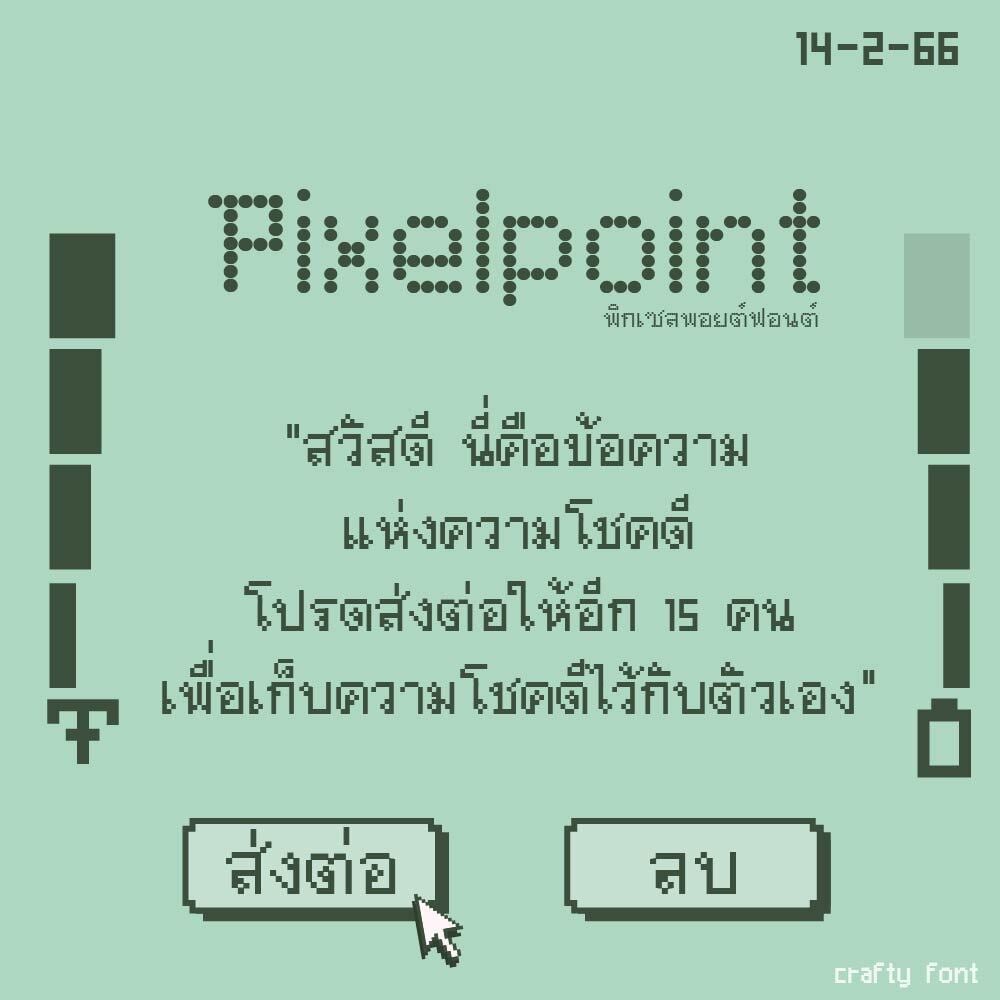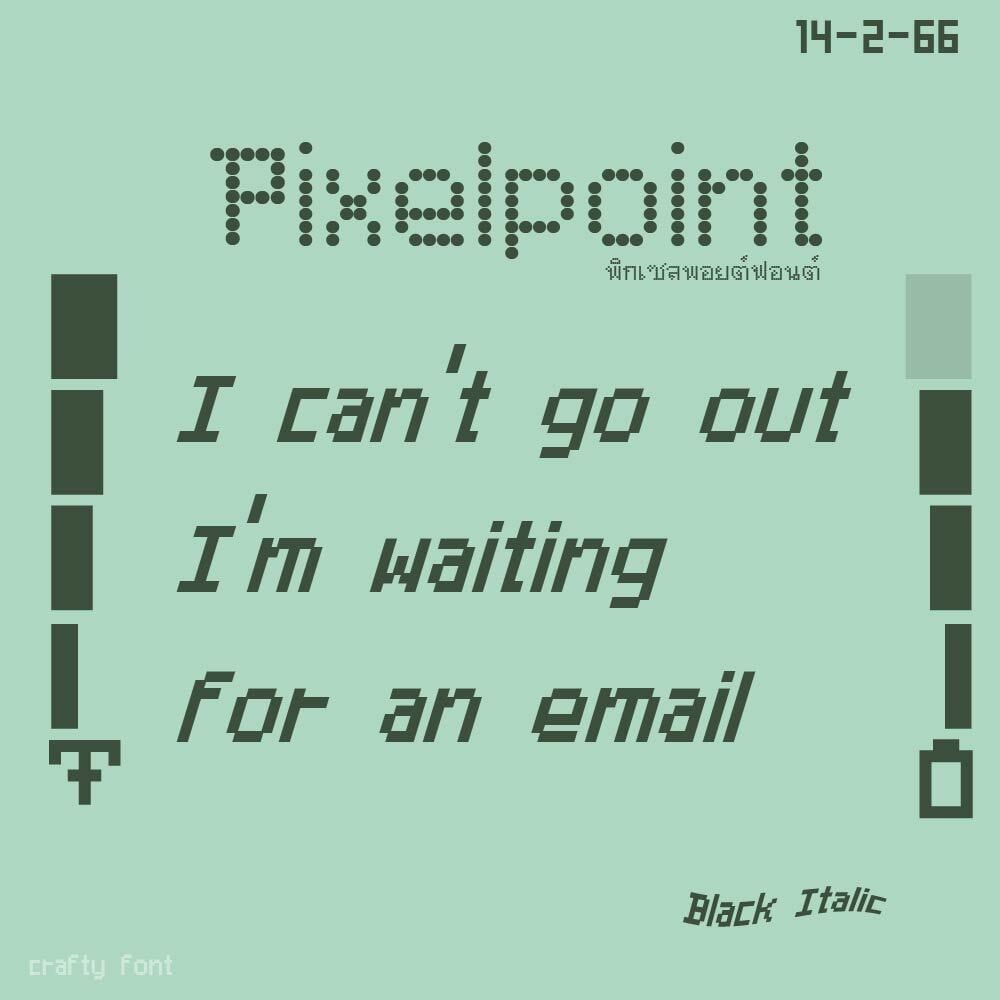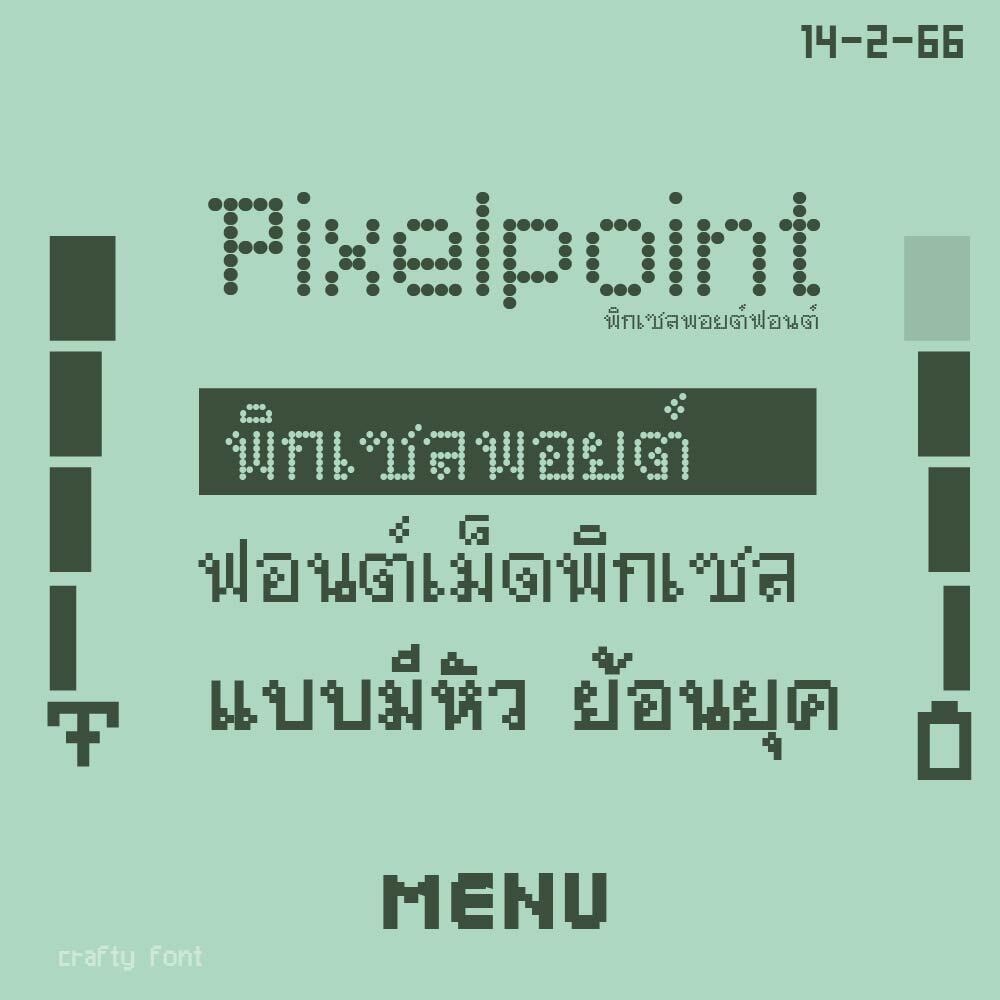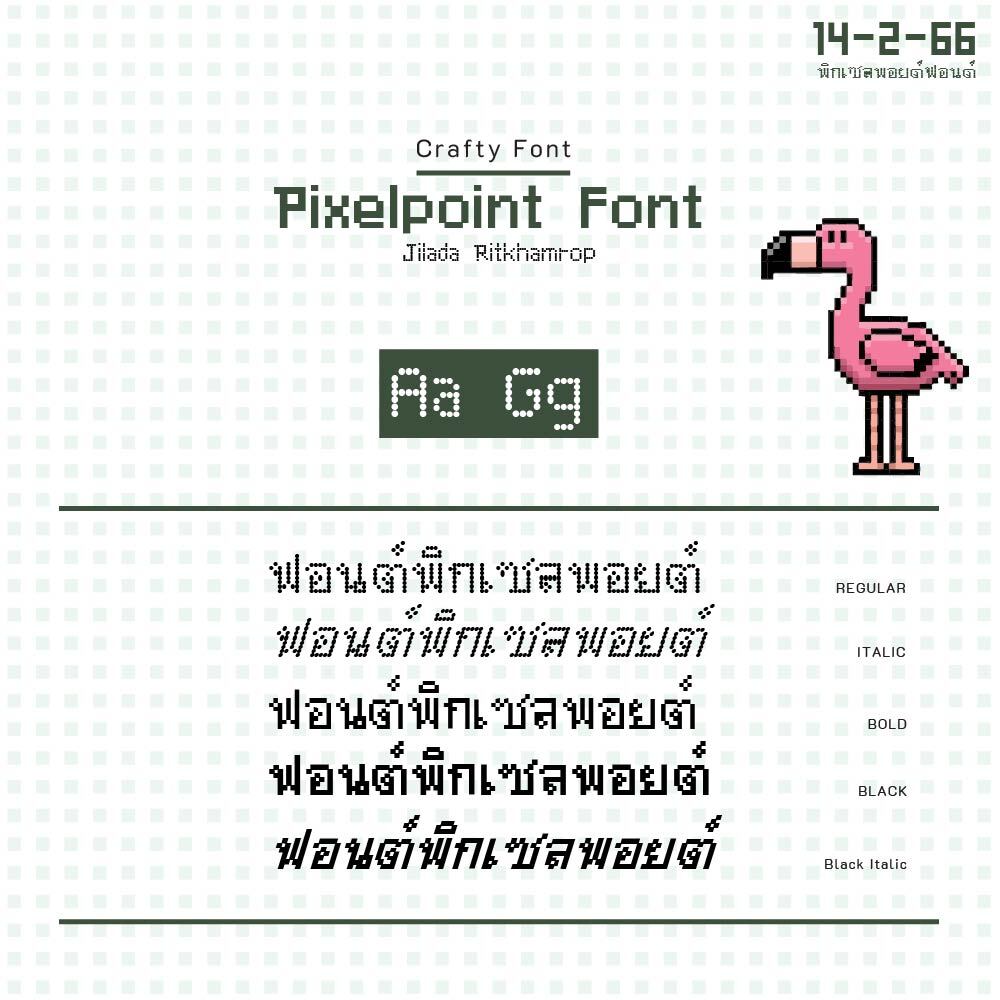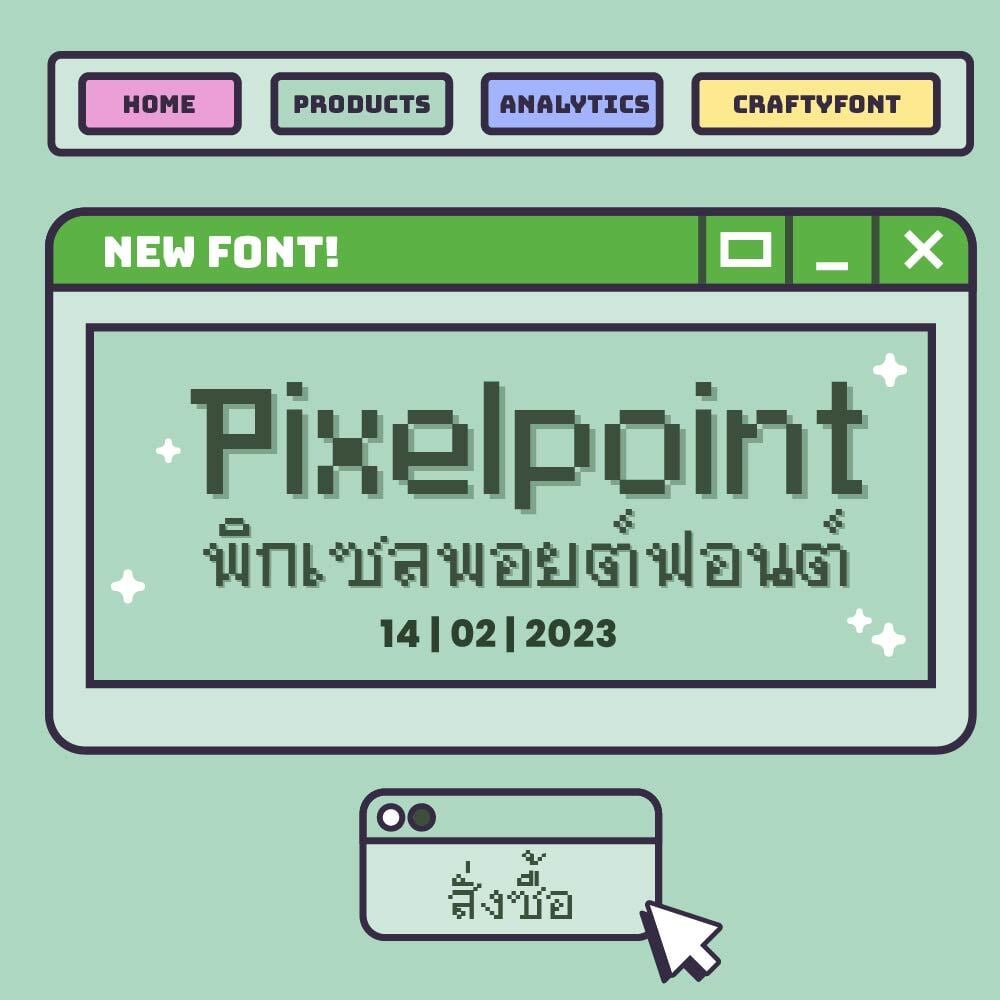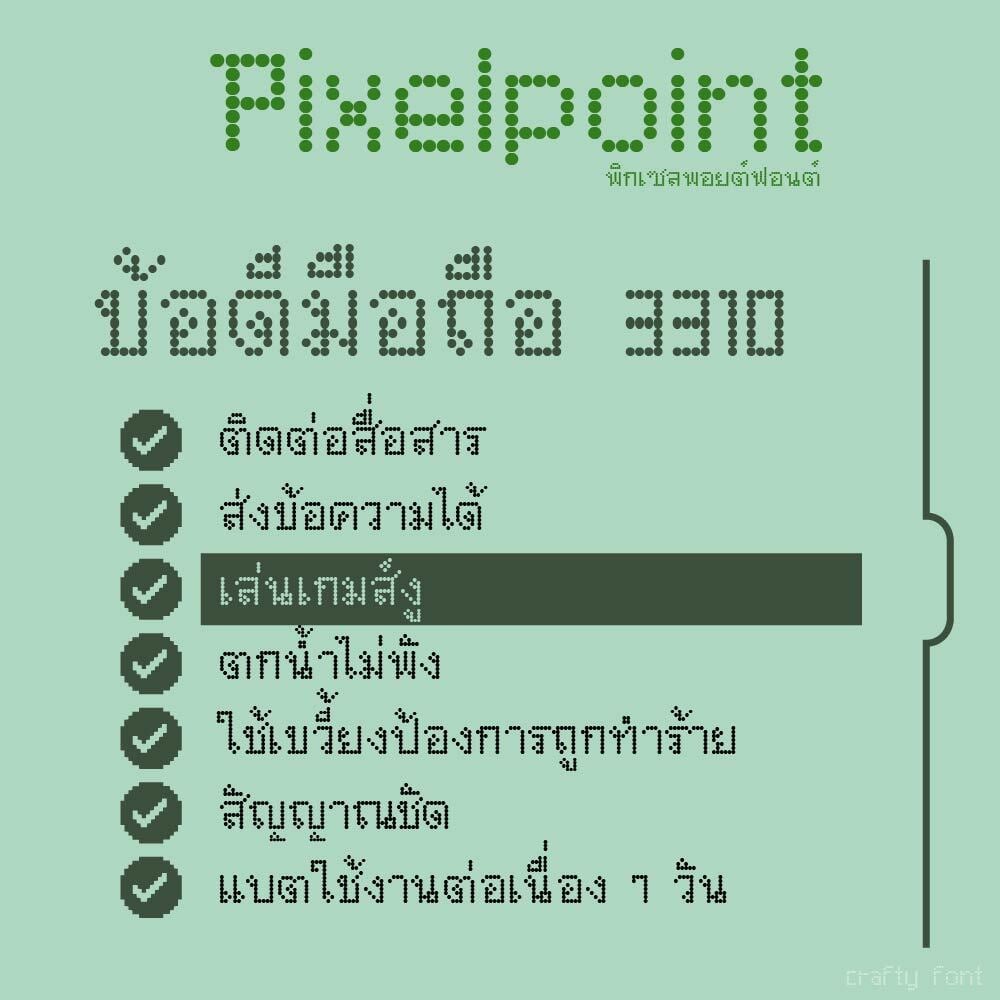
Pixelpoint Font (ฟอนต์พิกเซลพอยต์)
ฟอนต์เม็ดพิกเซลต่อยอดมาจากฟอนต์ Pixellet โดยทำให้ pixelpoint เป็นแบบมีหัว พิกเซลพอยต์ มีตัวปกติ (เม็ดพิกเซลกลม) ตัวหนา ตัวทึบ ตัวเอียง และตัวทึบเอน :)